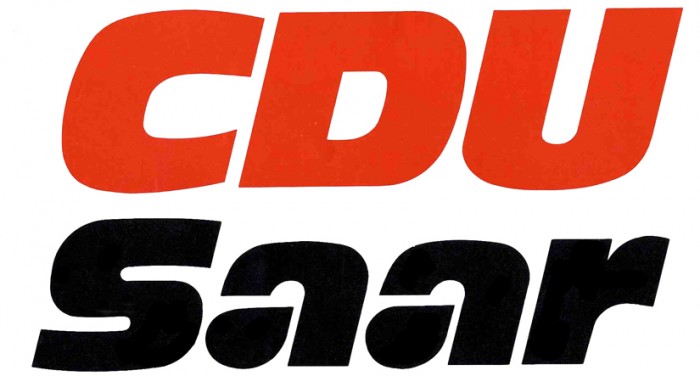
Schriftart oder Gestaltung?
kann mir jemand bei diesem Logo weiterhelfen? Ist von der CDU - Landesverband Saarland aus dem Jahr 1975.
Ist für die Unterschrift "Saar" eine bekannte Schrift verwendet worden oder ist dies eine Gestaltung einer Werbeagentur? Was meint ihr?
Habe auch eine Runde im Netz gesucht und bin dabei auf den Hinweis gestoßen, dass die Antique Olive lange Zeit von der CDU/CSU verwendet wurde...
… dass die Antique Olive lange Zeit von der CDU/CSU verwendet wurde...
… und, historische Fußnote am Rande, von der CSU-Ausgründung DSU.
Hmmmh jetzt habe ich noch kurz eine Frage: Wie würdet ihr denn die Gestaltung beschreiben?? Die Punze des a's ist ausgefüllt?? Ersetzt als an einen Tropfen erinnernd?